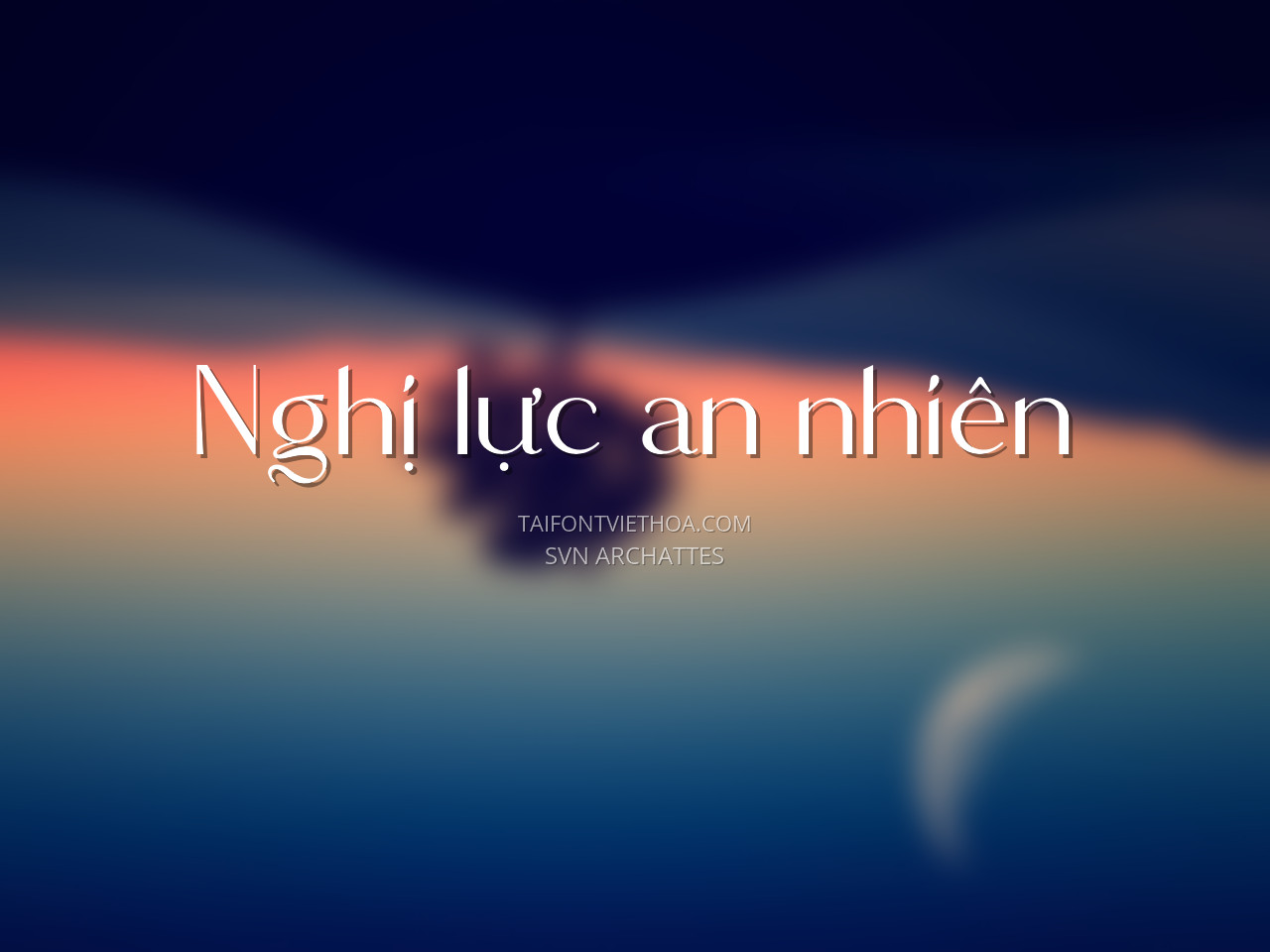
Font việt hóa SVN Archattes
Giới thiệu về font SVN Archattes – Kiểu chữ serif thanh lịch, mềm mại và tinh tế
SVN Archattes là phiên bản Việt hóa của font Archattes – một kiểu chữ serif mang phong cách thanh lịch, mềm mại và rất tinh tế. Font được thiết kế với các nét chữ uyển chuyển, cân đối và có độ tương phản hài hòa, phù hợp cho các dự án thiết kế thương hiệu, in ấn và truyền thông cao cấp.
Phiên bản Việt hóa của SVN Archattes đã được Taifontviethoa.comchăm sóc kỹ lưỡng, hỗ trợ đầy đủ dấu tiếng Việt cùng hơn 80 ngôn ngữ khác. Font giúp các nhà thiết kế dễ dàng áp dụng trong nhiều lĩnh vực đa dạng mà vẫn giữ được vẻ đẹp chuyên nghiệp và thanh lịch.
Thiết kế serif mềm mại – Ứng dụng rộng rãi trong thương hiệu và xuất bản
SVN Archattes sở hữu cấu trúc serif với các nét chữ mềm mại, đường cong uyển chuyển và độ tương phản hài hòa. Font phù hợp cho đoạn văn bản dài và tiêu đề, giúp tăng tính thẩm mỹ và sự trang trọng cho thiết kế. Phong cách của Archattes mang đến sự hài hòa và tinh tế cho mọi sản phẩm thiết kế.
Ứng dụng lý tưởng: thiết kế nhận diện thương hiệu, bìa sách, tạp chí, brochure, thư mời, danh thiếp và các ấn phẩm quảng cáo cao cấp. Ngành nghề phù hợp: thời trang, mỹ phẩm, nội thất, giáo dục, xuất bản và các thương hiệu định vị theo phong cách thanh lịch, mềm mại.